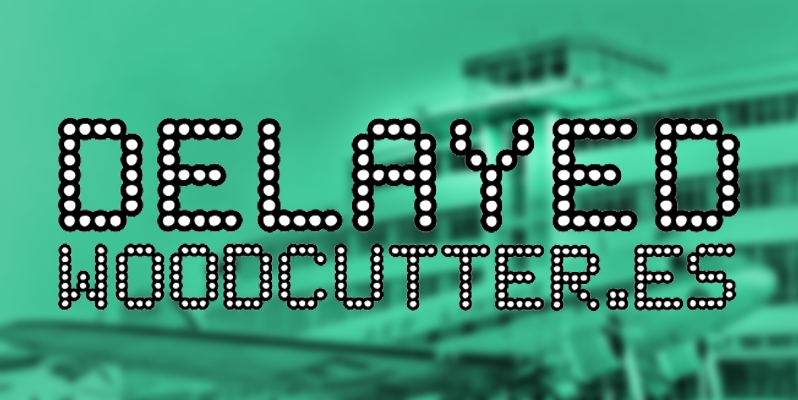
A fonte Delayed é uma escolha perfeita para seus projetos digitais que buscam um toque único e arquitetado com precisão pixel art. Inspirada no estilo do MMXV (ano 2019) de arte ilustrativa, a fonte Delayed captura a essência moderna e vibrante de Hamilton’s criação, oferecendo uma experiência visual intrigante em projetos digitais que buscam um contraste marcante. Ainda mais interessante é seu aspecto minimalista que se adapta perfeitamente às interfaces modernas. Os detalhes precisos e a riqueza de cores da fonte Delayed proporcionam um toque personalizado sem comprometer o design simples, tornando-a uma escolha ideal para qualquer aplicação gráfica online ou offline. A receita é essa: com sua característica única e seu design elegante, a fonte Delayed pode transformar as suas ideias digitais em algo verdadeiramente único e incrivelmente visual.